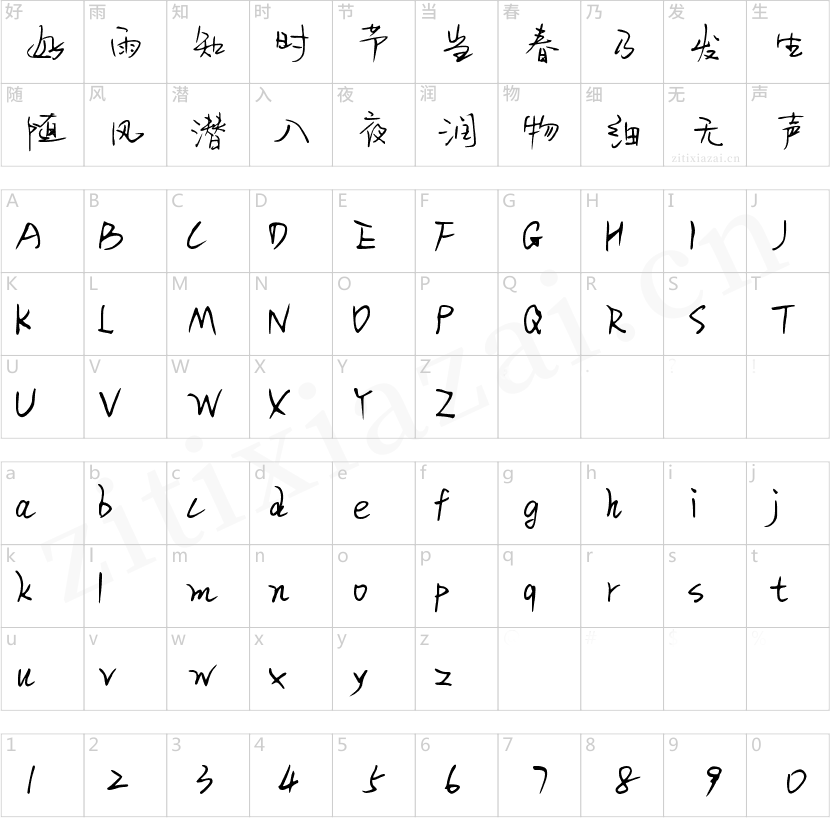
Aa花语鸢尾的思念
Aa花语鸢尾的思念字体
Aa花语鸢尾的思念是一款非常具有艺术性的字体,它的设计灵感来源于对古典艺术的研究,同时又融入了现代字体设计的元素。字形优美,笔画粗细变化自然,给人以大气、典雅的感觉。Aa花语鸢尾的思念是一款既传统又现代的字体,它的设计充满艺术感,美观大方,实用性也非常强。无论是对于设计师还是对于普通读者来说,都是一种非常不错的字体选择。Aa花语鸢尾的思念适合用于具有艺术感的场合,比如海报、宣传单张、书籍封面等。由于其字形流畅且具有动态感,也适合用于大量的文本排版,如报纸、杂志等。